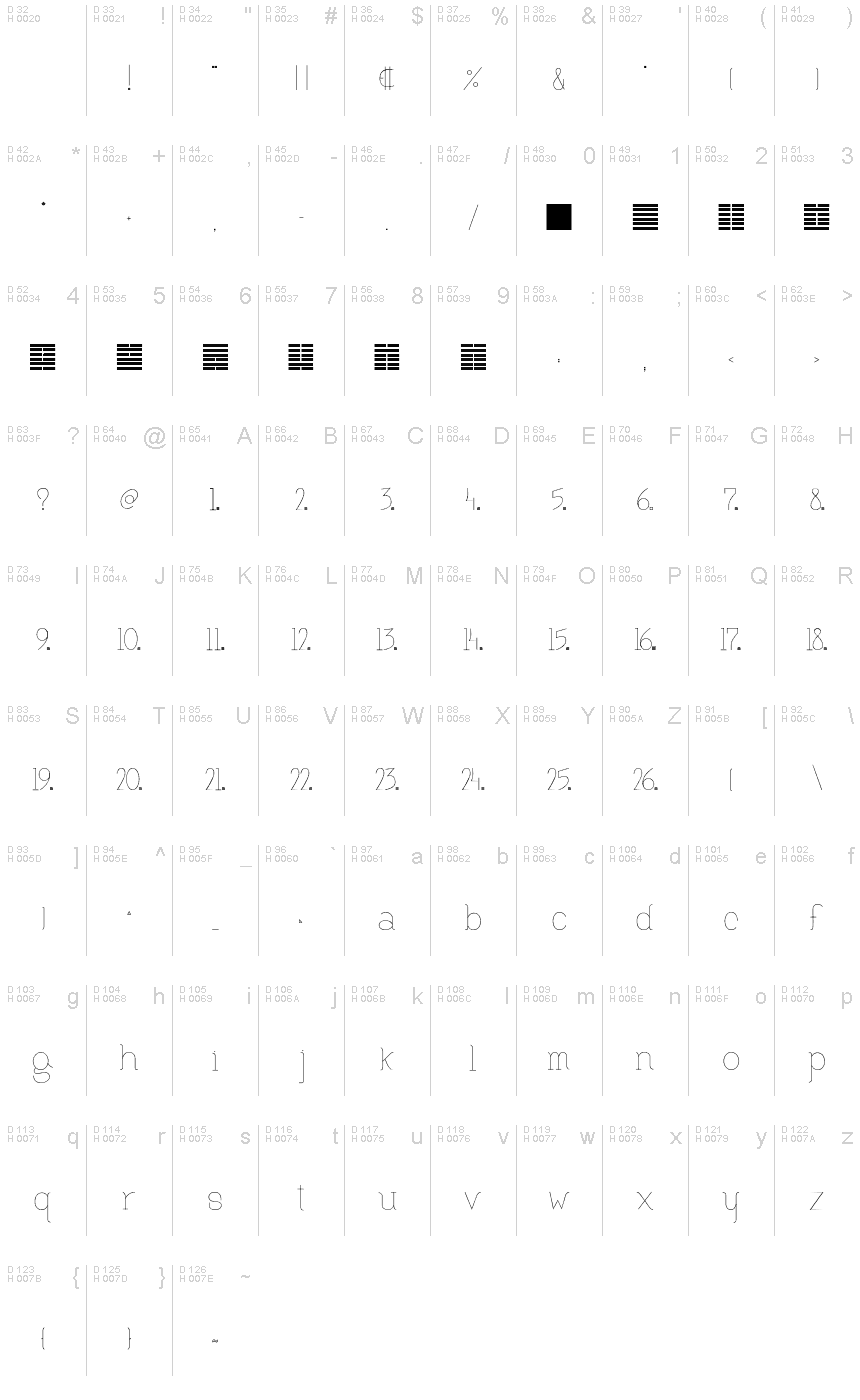
to whom it may concern type
esta fonte foi criada em inspirao ao projeto musical iamamiwhoami. a caixa alta dessa fonte numrica, cada letra corresponde ao seu lugar na fila dos alfabtos, logo a letra A ser 1. e F ser 6. os nmeros de 0 a 9 so simbolos do I Ching, livro dos Hexagramas, segundo a teoria utilizada nas preludes que antecediam o primeiro disco da banda. com conceitos da era bounty e seus cdigos secretos nos ttulos da msica, at as grandes ondas azuis de blue nas serifas da fonte, to whom it may concern type uma tipografia totalmente experimental. para ser usada em tamanho de corpo menor que 24 ser necessrio uso de stroke ou contorno na mesma para que fique legvel. no use efeito bold ou italic, os mesmos podem destorcer a fonte. criada e vetorizada por mim, designer, felipe. para quem se interessar!